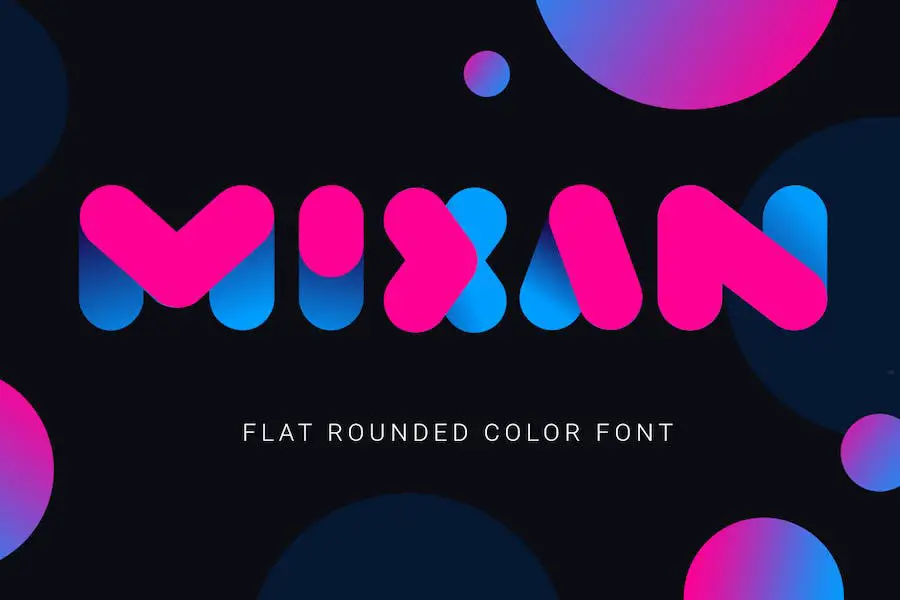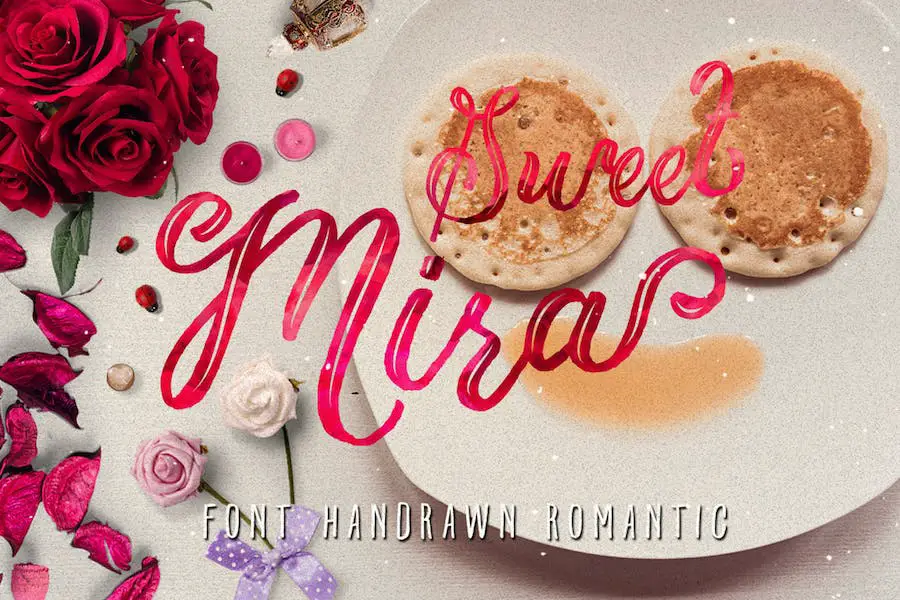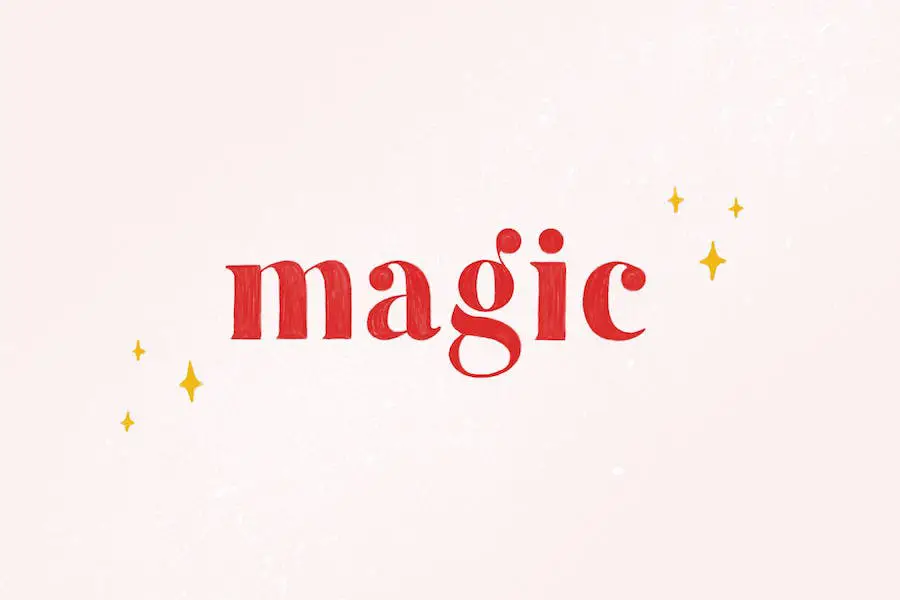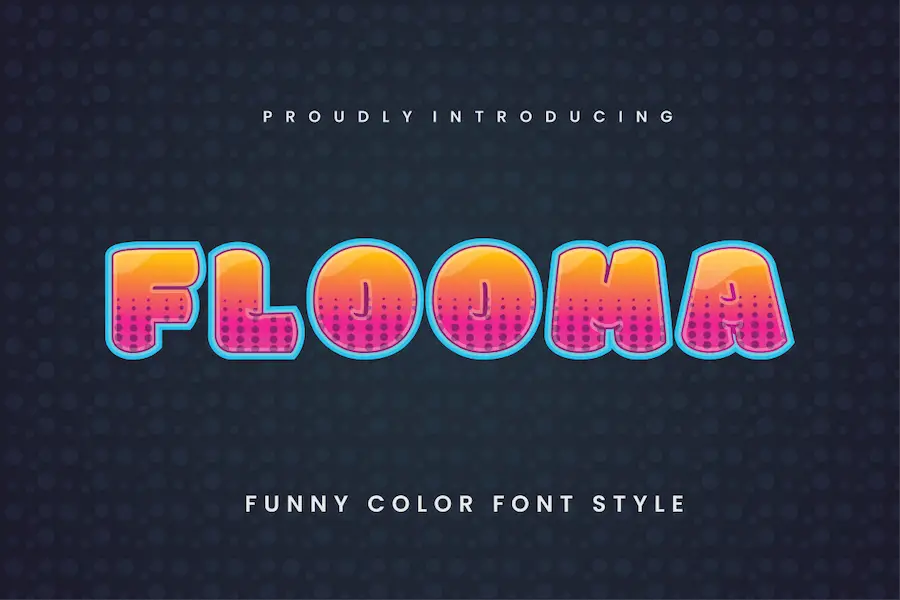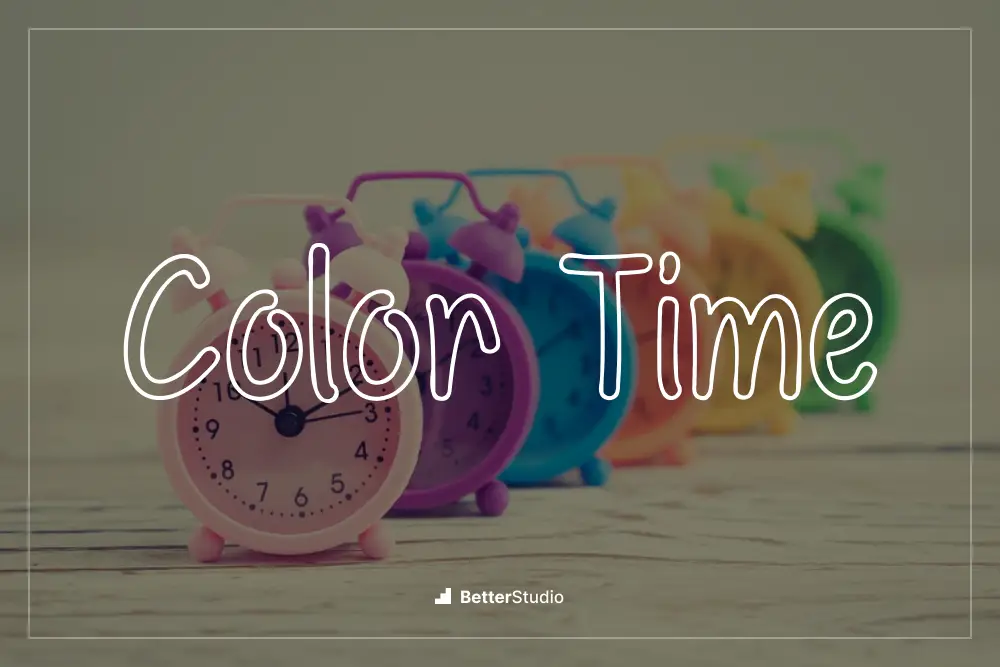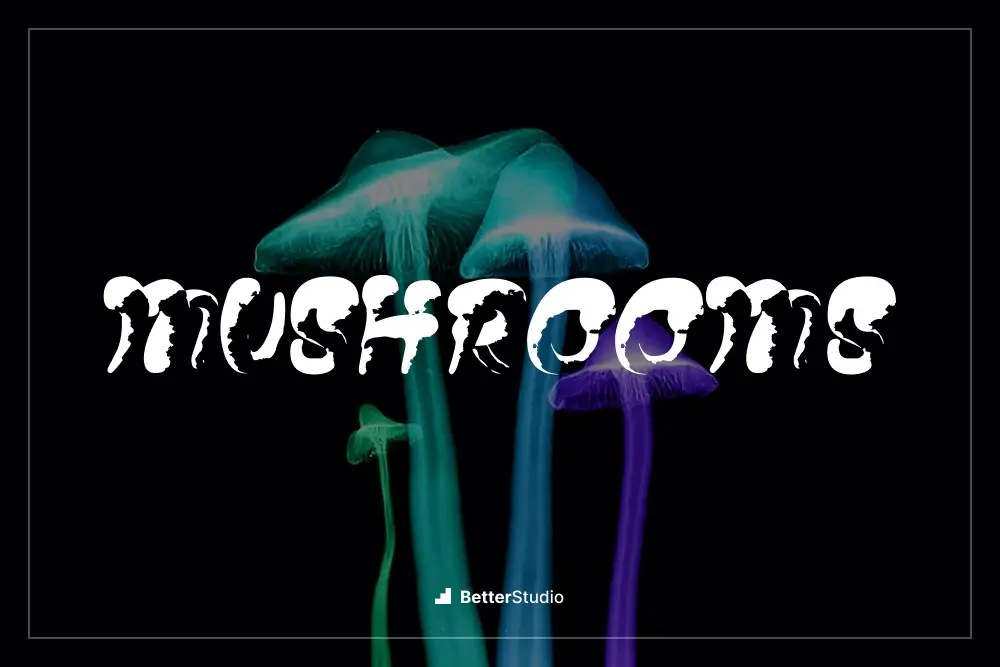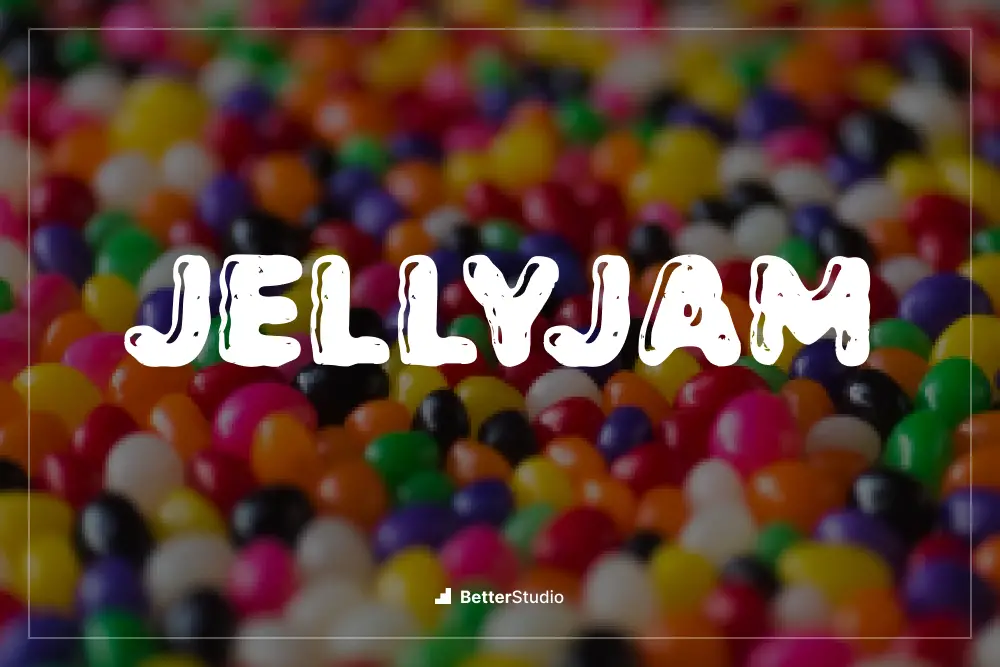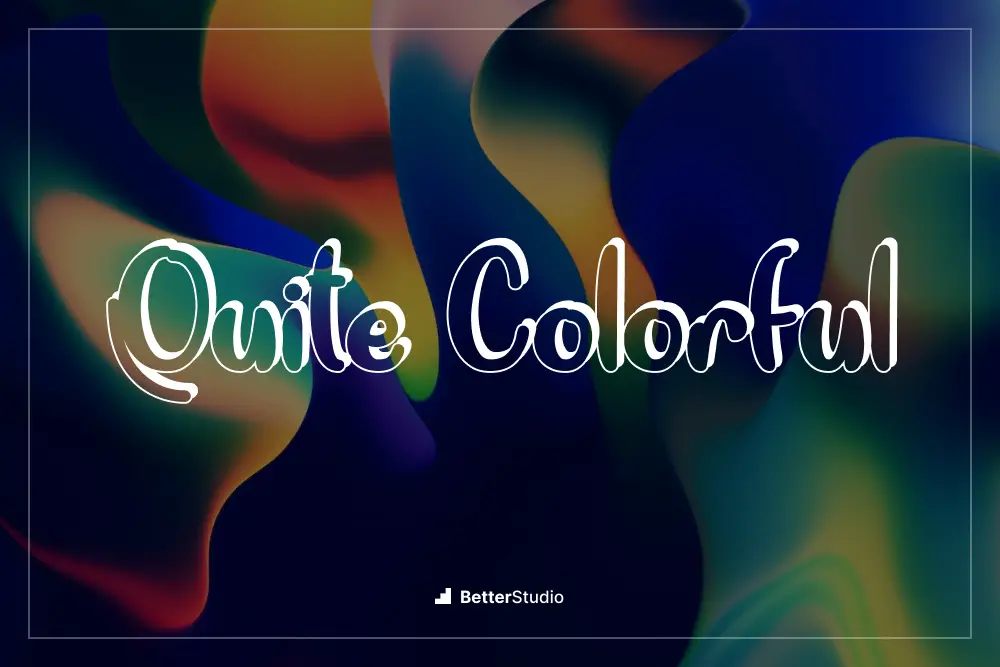
15 migliori font a colori del 2023 (gratuiti e premium)
Pubblicato: 2023-08-07Sei un graphic designer e desideri migliorare il design dei tuoi progetti? Bene, non cercare oltre! In questo post del blog, esploreremo i 15 migliori font a colori che possono portare i tuoi progetti al livello successivo.
Ma prima di immergerci nell'entusiasmante mondo dei caratteri a colori, potresti chiederti: "Cosa sono esattamente i caratteri a colori e perché dovrei usarli?"
I caratteri a colori sono una tendenza relativamente nuova nel settore del design che consente ai designer di incorporare colori vivaci e accattivanti all'interno della loro tipografia. A differenza dei caratteri tradizionali che sono disponibili solo in nero o in scala di grigi, i caratteri a colori aprono un intero nuovo mondo di possibilità creative.
Possono essere utilizzati in vari progetti come branding, pubblicità, design di siti Web e altro.
Ora, entriamo nei dettagli nitidi di questo articolo! Abbiamo curato un elenco dei 15 migliori font a colori che puoi aggiungere alla tua libreria di font. Ogni carattere ha il suo stile unico, colori vivaci e versatilità, che li rendono perfetti per qualsiasi progetto di design che hai in mente.
Dai caratteri giocosi e stravaganti a quelli moderni ed eleganti, ce n'è per tutti i gusti. Quindi, sia che tu stia cercando di aggiungere un tocco di colore ai tuoi progetti o di creare una grafica visivamente sbalorditiva, questi caratteri a colori ispireranno sicuramente ed eleveranno il tuo lavoro.
Preparati a liberare la tua creatività mentre esploriamo questi 15 fantastici caratteri a colori. Immergiamoci!
I migliori font a colori premium
Stai cercando di elevare i tuoi progetti di design? Non guardare oltre la nostra selezione selezionata dei migliori font premium. Dai un'occhiata a questi caratteri e guarda i tuoi disegni prendere vita!
Realita
Realita è un font unico e bellissimo, perfetto per vari progetti come monogrammi, matrimoni, citazioni, loghi, scarabocchi, intestazioni e titoli. Questo carattere colorato è disponibile in entrambi i formati TTF ed EOT, consentendo una facile compatibilità tra diversi software e piattaforme di progettazione.
Inoltre, Realita presenta anche una variazione floreale, aggiungendo un tocco di eleganza a qualsiasi design. Con le sue scritte chiare ed eleganti, questo carattere farà sicuramente risaltare i tuoi progetti.
E se stai cercando di aggiungere un effetto ombra, Realita include anche una versione ombra in entrambi i formati TTF ed EOT. Dai ai tuoi disegni un aspetto fresco e vibrante con il carattere Realita.
carta colorata
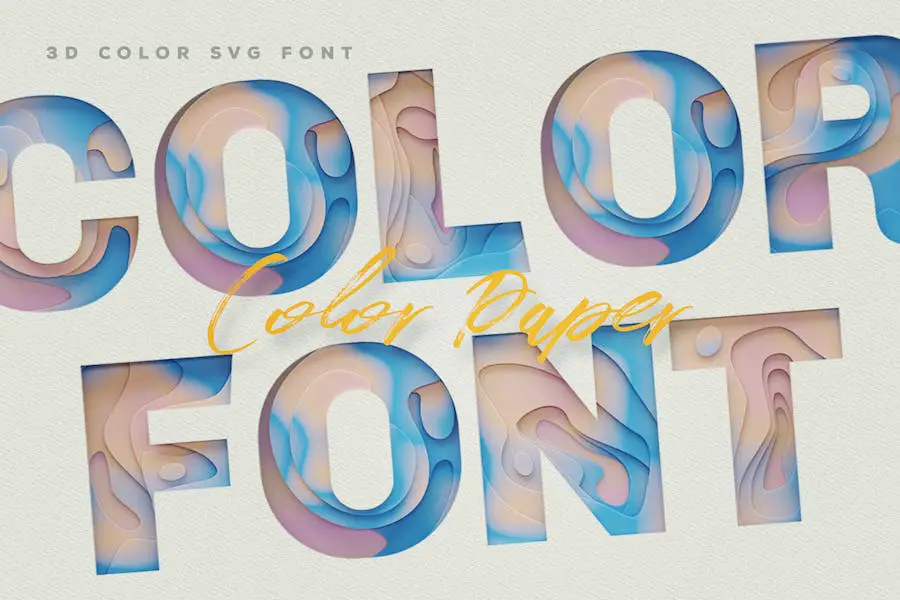
carta colorata è un set di 4 incredibili font a colori 3D che eleveranno i tuoi progetti a nuovi livelli. Questi caratteri sono perfetti per aggiungere un tocco vibrante e dinamico ai tuoi progetti.
Colori pastello
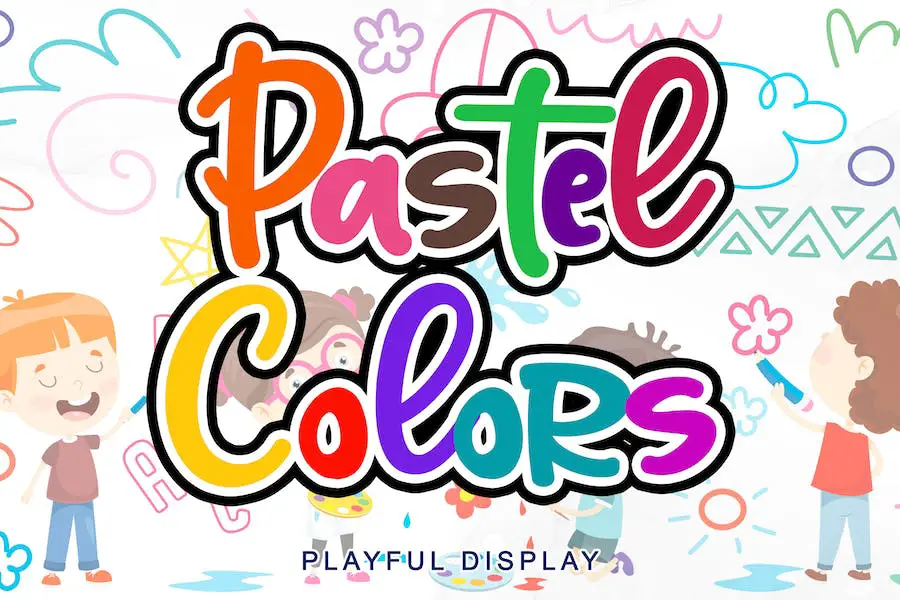
Pastel Colors è un carattere di visualizzazione delizioso e affascinante che aggiunge un tocco di divertimento a qualsiasi progetto di design.
Con il suo stile giocoso e l'eccellente leggibilità, è perfetto per varie applicazioni come cartoline di Natale, branding, cancelleria, design di blog, arte personalizzata, timbri personalizzati, goffratrici personalizzate, libri, abbigliamento, imballaggi, titoli e molto altro ancora!
Questo font darà senza dubbio un aspetto unico e un aspetto sorprendente alle tue creazioni.
Ciò che distingue Pastel Colors è la sua codifica PUA, che ti consente di accedere senza sforzo a tutti gli adorabili glifi che offre. Inoltre, viene fornito con una vasta gamma di legature, aggiungendo ancora più versatilità ai tuoi progetti.
Ti innamorerai rapidamente del suo stile distintivo e senza tempo, che lo rende la scelta perfetta per creare design eccezionali e di grande impatto visivo.
Colore caramella
Candy Color è un carattere di script di visualizzazione vivace che aggiungerà carattere e consistenza ai tuoi progetti di design. Questo font utilizza la più recente tecnologia OpenType-SVG, che gli consente di catturare magnificamente le pennellate.
Che tu stia lavorando a un progetto di branding, cancelleria per matrimoni, layout di riviste o grafica pubblicitaria, Candy Color porterà il tocco perfetto di divertimento e personalità.
Con 26 caratteri, numeri e segni di punteggiatura, Candy Color offre una gamma versatile di opzioni. Ma non è tutto: ogni stile di carattere viene fornito con una controparte "alternativa", che ti offre un set aggiuntivo di 26 caratteri.